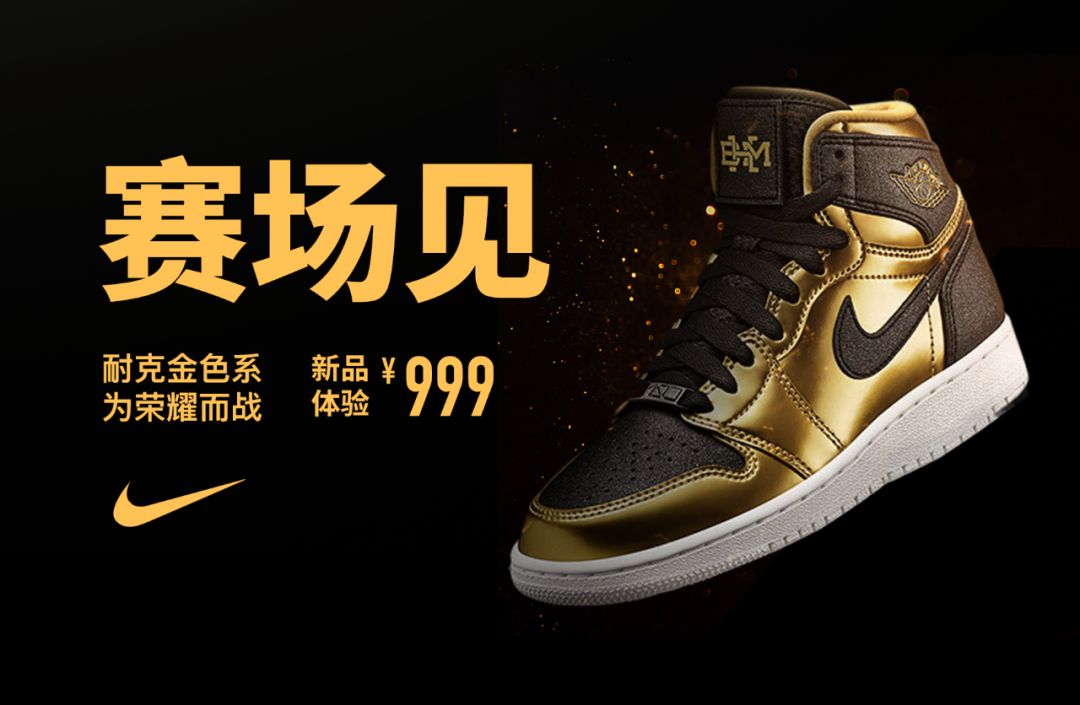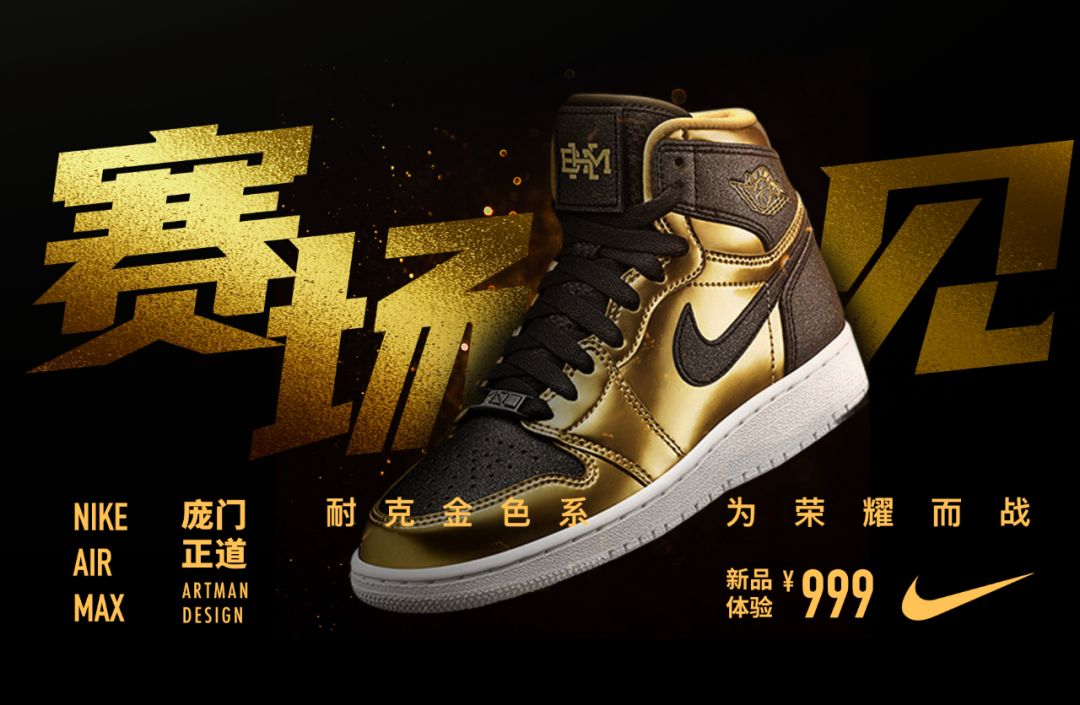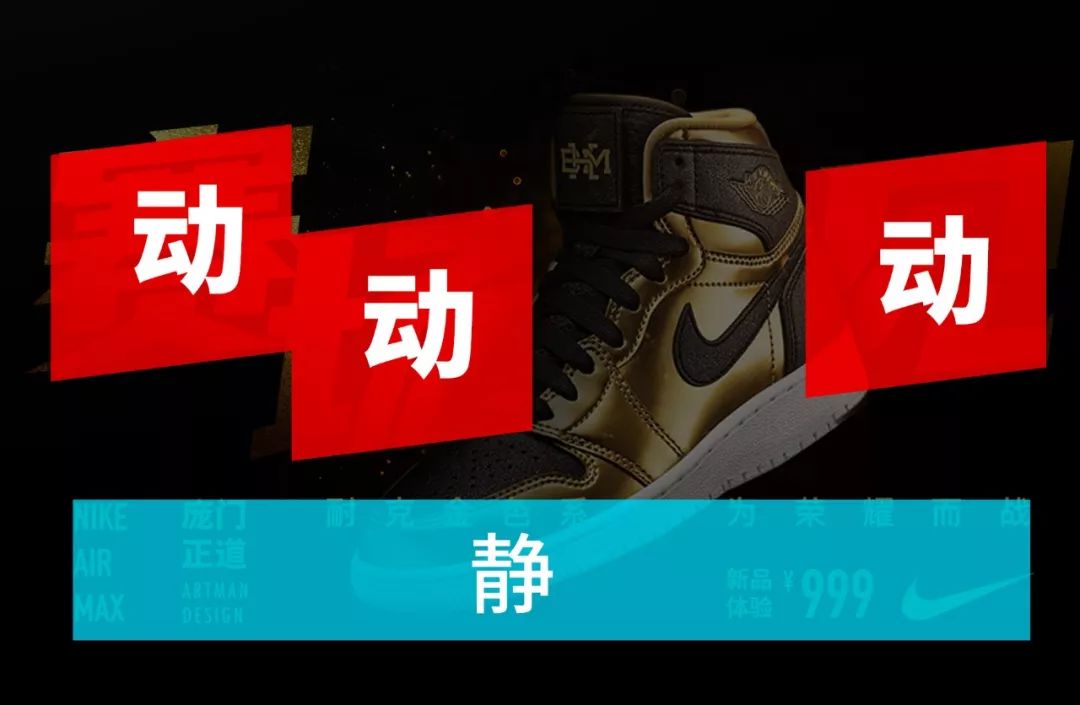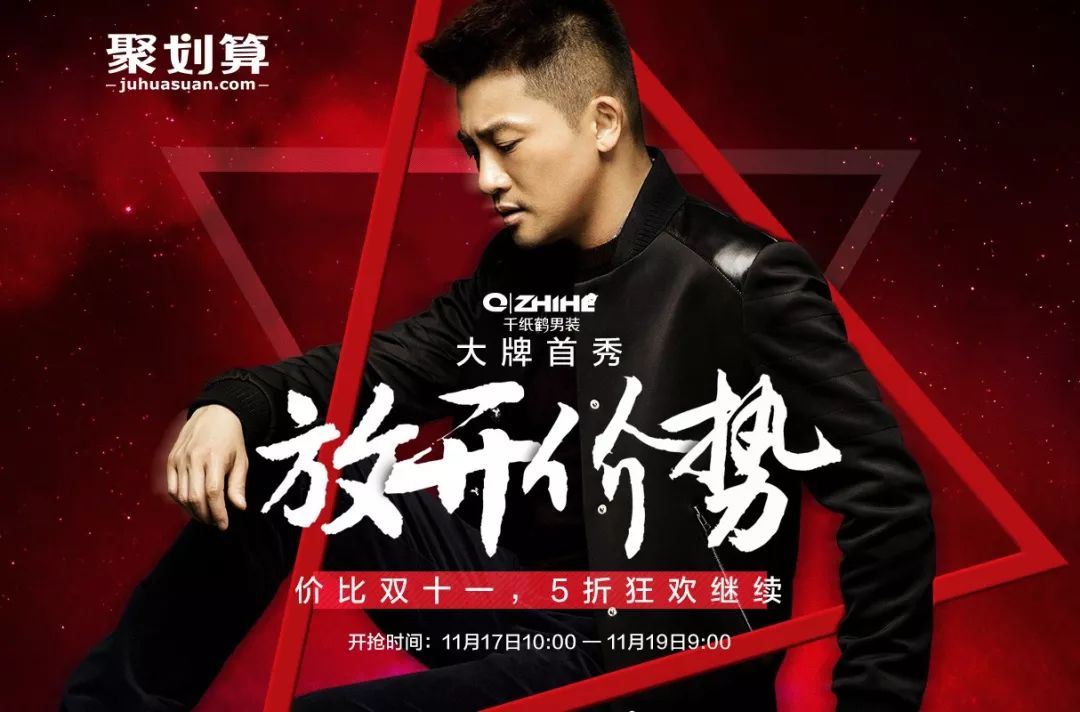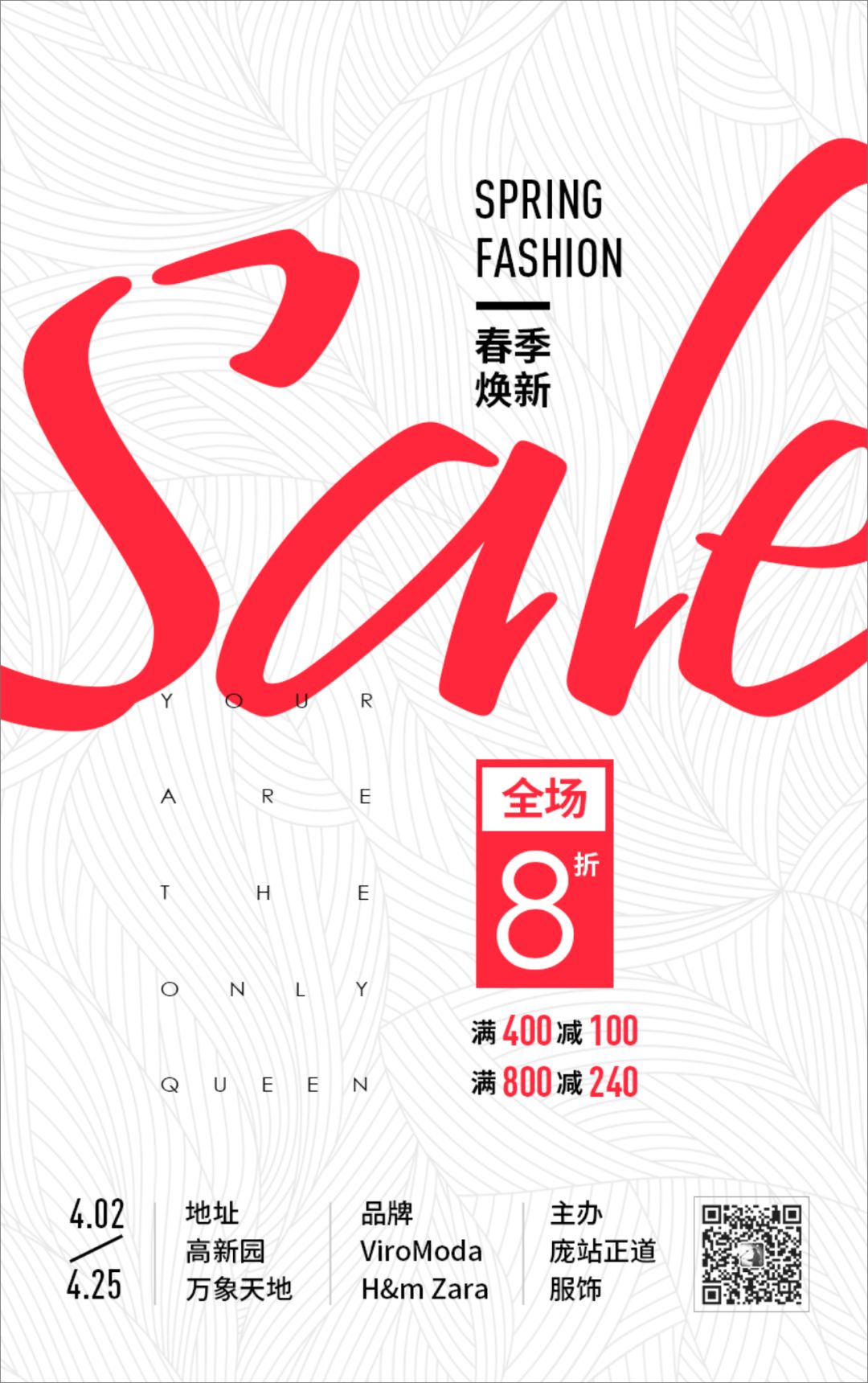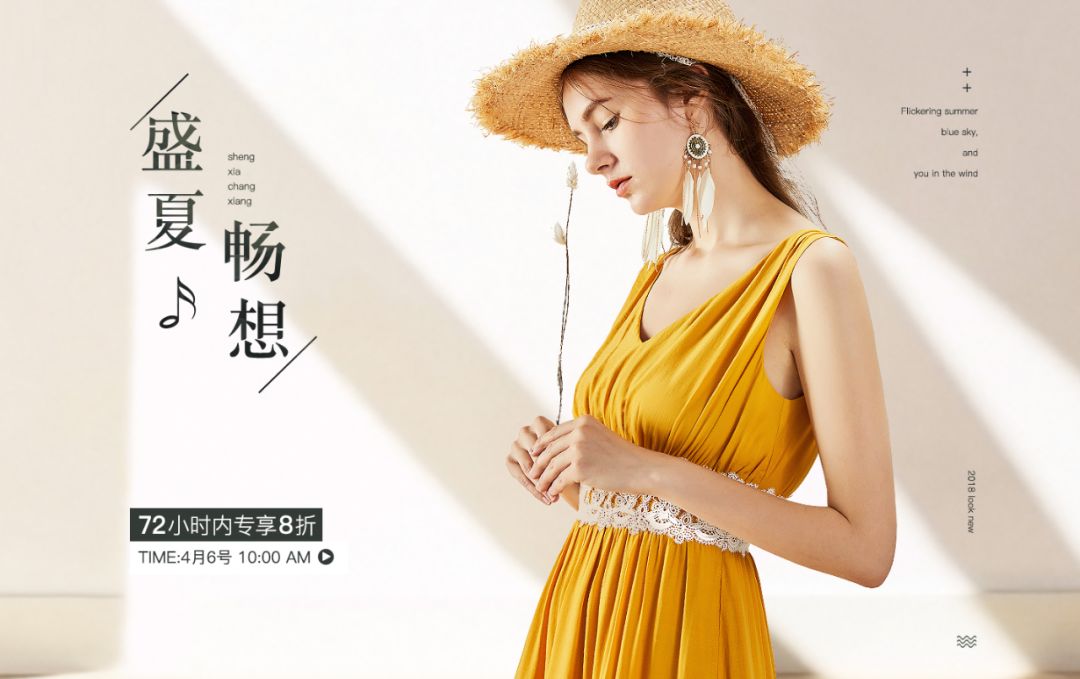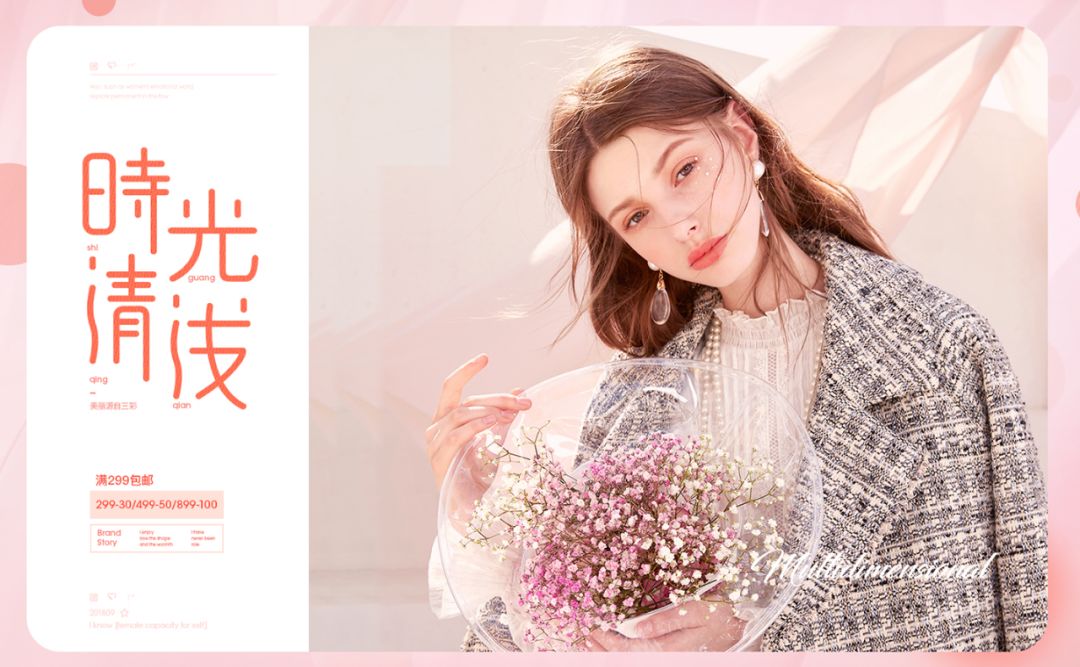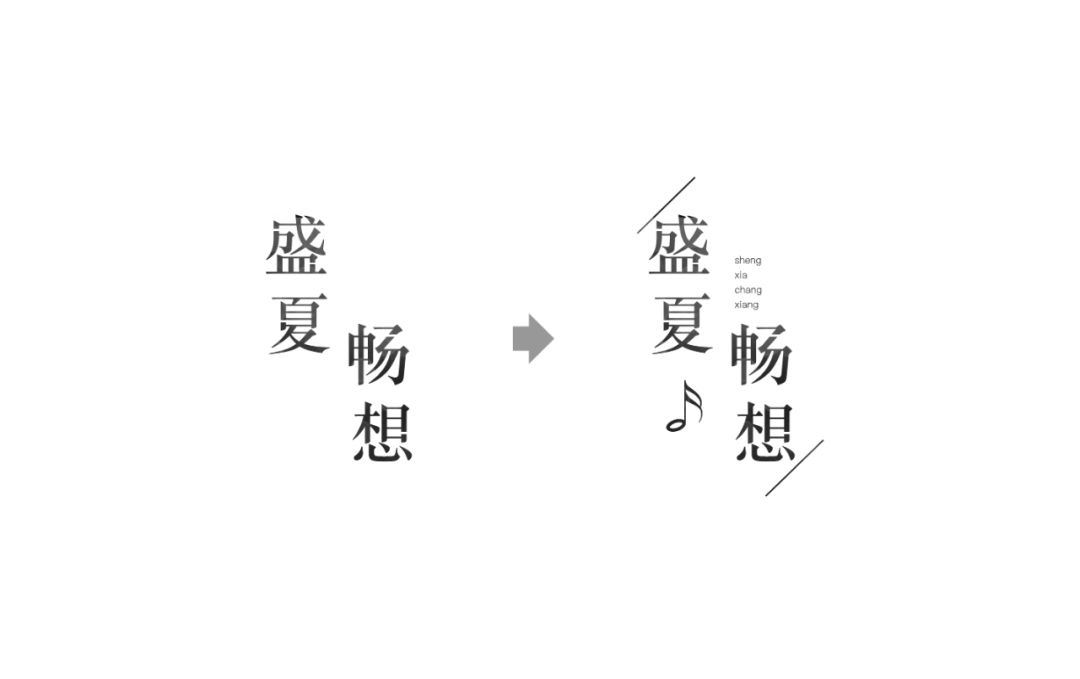
电商广告标题不会设计?这篇内容告诉你
今年的第一期干货教程新鲜出炉。
不少新手设计师在做电商广告的时候,最头疼的就是标题怎么做?做得太简单了没有视觉冲击力,做得复杂了,又担心过于花俏,影响到信息传达。那怎么能让我们的设计恰到好处呢?
今天的文章我就给大家讲讲电商广告标题设计中常用的实用技巧。
OK,干货走起。。。
在写具体的方法之前,我们得先知道标题设计的一些基本原则。
一、标题要准确、清晰。
对于大多数电商广告来说,讲究的是转化率。就是说用户看一眼就得知道这是卖什么的。
所以在任何时候都是:
在做完一张广告图之后,请再多看几眼,确认标题将最重要的信息最大程度的展示出来了。
二、标题要层次分明。
在将内容表达清晰之后,更高一级的要求就是将信息更快速的传达。
要做到快速、高效,在设计的时候就得拉开层次,用对比的方式将信息分层,最重要的信息用最强烈的视觉表现手法。
例如下面这张图,它其实也有大小对比,但是混乱的排版造成标题就糊成一团,简直无法阅读,更不要说将信息高效传达了。
怎么判断标题的层次清不清晰?
记住我这张视觉漏斗图:
好了,如果你设计的标题符合上面两条基本准则,那么,你可以开始考虑它的视觉风格了!
下面我给大家总结了几招特别实用的标题设计技巧,来吧!
我们常说电商广告要燃、要炸,这没错,但是具体怎么燃怎么炸,还是要讲究方法的。如果一个画面的所有元素都在“炸”,那整个画面肯定就要被炸毁了。所以我们一定要有控制。
一般来说,我们都会提取出标题中比较重要的部分,如促销数字,商品卖点,用比较动感、强烈的视觉方式去表达,而一些辅助的信息,则用比较平稳一些的方式去处理,这样动静结合的设计手法就有强弱对比,既让重点信息突出了,整个设计也比较协调。
动静结合的方式有很多种,我给大家总结一下:
副标题静,主标题动:
次要文案静,重要文案动:
画面主体静,标题动:
标题静,背景动:
上面的这些方法你都可以举一反三,反复去尝试更适合你自己的方式。
记住,
动,产生更强烈的视觉效果。
静,有更平稳的构图,更好的阅读体验。
下面来看具体的实操案例。
先看原稿:
对于一个运动主题的设计,原图明显过于安静了,按照上面的方法,我们可以采用“主标题动,副标题静”的方式来优化这个广告。
最终效果:
怎么样?动静结合是不是挺爽!
在之前的教程中我讲过,加入色块可以丰富画面的层次。
在标题设计中,我们也可以加一些基本的几何形,让文字信息更加聚焦,也让我们的排版的时候,找到可以依据的形式。
在实际的应用中,我们一般选用正方形,圆形等比较规正的图形即可,一些奇奇怪怪的异形慎用。
另外,几何图形除了可以聚焦信息之外,也可以很好的填充空间,让画面显得饱满。
来看实操案例。
下面是一张干干净净的女装广告,很中规中矩的设计。
仔细观察一下,会发现整个画面的元素之间缺少一些关联性,显得有点拼凑感,同时整体画面也不够饱满。
为了解决上面的问题,我加入一个圆形的色块到画面中,将标题信息全部整合到圆形里。
优化过后,两个模特图之间有了过渡,所有的文案信息全聚合到圆形之中,明显画面的层次感更清晰了。
OK ,下一招。
标题要大!当你听到这样的反馈时,先别着急着骂需求方是土包子。
对方可能只是觉得你的设计力度不够,他没法说出更专业的词汇,所以只能这么直白的来描述自己的需求。
大标题也未必就丑,相反的,只要处理得当,大标题可以营造强烈的视觉冲击力,让整个设计饱满、有力度!
来,动手做一个案例。
下面这双运动鞋的主打卖点是色彩,如果按常规排版我们可以得到这样一个画面。
显然这是一个不犯错的设计,但是太过于平淡,很难让人留下很深的印象。
我将标题提取出来,用更大的字号来展示,然后将商品放到画面正中间,这样整个画面的重点就更突出。
最后我们看到,修改过后的画面,明显更具视觉冲击力。
就问你,帅不帅?!
好了,继续看下一招。
广告标题很容易陷入一个误区,就是觉得标题简简单单就好,少做少错。对于这种只想考60分的同学,我当然要给一鞭子!
简洁≠简单,即使简洁的设计,也可以做得视觉上很丰富。把简洁的设计做成单调、平淡,那只是你能力的问题。
在实际的设计中,我们可以用小字,点,线条,这样极其简单的装饰性元素,来使得标题的排版更有层次感。
来看看具体案例:
这些小元素的加入,可以让标题显得更精致,有细节。做起来都十分简单,但是对于页面效果的提升又非常明显!
用线来条修饰标题的造型,化小字为点元素,见缝插针的对主标题进行补充。
这些小小的装饰元素,除了让排版更有层次感之外,也让整个画面显得更饱满!
来看看实操案例。
下面是一张意境非常唯美的图片,所以我们很容易想到标题要做得偏文艺小清新一些。
只要随便打几个字上去,就是一张不错的设计稿。
不过如果想让标题更能体现出画面的气氛,我们可以动动心思,利用上面学到的方法,通过文字的变化,再加一些线条来丰富一下版式。
优化完之后,标题和画面的气质更加统一和谐。
做设计最忌讳的事情就是一成不变,不愿意构想新东西,也就意味着你的设计水平停滞不前了。所以对细节的雕饰能够体现一名设计师的用心程度。
在广告标题的设计上,一些细节的变化可以让整个设计变得趣味横生,这些变化可能是简单的旋转一下,或者改个颜色等,却往往能收到意想不到的效果。
比如说,文字的残缺效果:
之前的教程做的演示案例:
笔划上做颜色的变化:
连笔以及笔划替换:
我只是随手列了几种,还有无限多种玩法供你想象。
这里我提醒一下大家,我们对文字进行视觉加工的时候,一定不能损失可阅读性,如果一个字被改得认不出来,那显然就是本末倒置了。
下面再来一个实操案例。
先看看初稿:
整体是非常简洁的风格,为了让画面更有设计感,我们可以对标题进行一些细节的改造:
在不影响文字识别性的前提下,我将一些笔划进行了删除,这样会使得文字更加图形化,有种被设计过的感觉。
来看看放在画面中的效果:
好了,
最后我们再来回顾一下广告标题的五种处理手法:
1、动静结合——动如脱兔,静若处子
2、色块——聚焦信息
3、大字——营造视觉冲击力
4、小字、点线——丰富排版层次
5、细节变化——妙趣横生